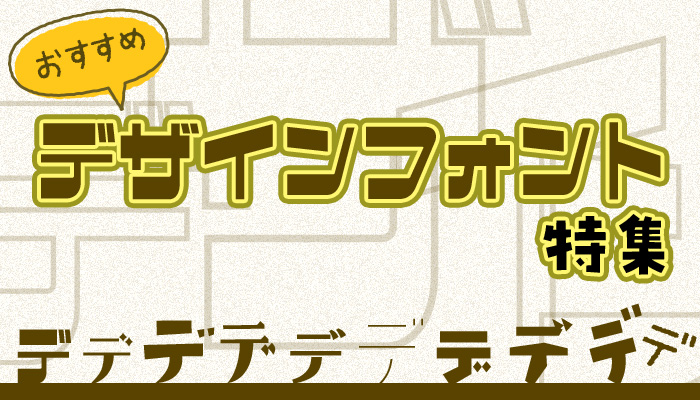
タイトルや見出しに最適! 個性が光るデザインフォントをご紹介
どっしりと太く強いインパクトがあるものから、かたちがユニークなもの、ゆるっとたリラックス感が楽しいフォントまで、色んな表情をもつデザインフォント。各ブランドから様々な雰囲気や特徴のデザインフォントを厳選してご紹介します。
注目を集めたいコピー、タイトル、見出しから、ポスター、チラシ、カタログ、Webサイト、動画、テロップ、アニメーションまで、いろんなシーンで活躍します。
デザインフォントでワンランクアップしたデザインを作りましょう!
鈴木メモ
空とひこうき
万年筆でさらりと書いたようなインクのようなにじみを生かしたはしり書きフォント。
花とちょうちょ
ペンで書いた手書き文字がベースのフォント。右上りの勢いと何より可愛らしいリアル手書き感が特徴。
パンダベーカリー
手描きのような自然なリズム感と見出しやパッケージにも最適なしっかりとした太さがある書体。
デザインシグナル
DSきりぎりす
切り文字のような大胆さを持ったデザインシグナルの一番人気。
DSあかり
角ばった律儀なフォルムと、明るく軽やかな雰囲気を両立する書体。
DSストロング
岩石のような固さ、力強さの中にも優しさを感じる、太く元気な書体。
ダイナフォント
DFロマン雪 A/B/立体
大正末期から昭和初期にかけての古典ロマンの雰囲気を再現した書体。
DF綜藝体 W5/W7/W9
ゴシック体をベースに独特のポップさを生みだしたデザイン書体。
DF金文体 W2/W3/W5
中国戦国時代の金文を元に神秘性や独創性を高め現代的な感覚で仕上げた書体。
楽フォント
遊妖体 (ゆうようたい)
点には抑揚、はらいには独特のカーブとユニークな遊び心に溢れ、どの文字も見ていて飽きないような書体。
凛松体 (りんしょうたい)
書道作品における毛筆の運びと墨によるダイナミックなウエイト表現にモダンなエッジを加えて、端正な面持ちの中にもしっかりとした芯が感じられる書体。
親剛体 (しんごうたい)
縦画と横画の線幅のコントラストによって生み出される圧倒的インパクトと、滑らかでやわらかいカーブの組み合わせが特徴的な書体。
ヤマナカデザインワークス
やわらかドラゴン
強くもあり、どこか柔らかい。そんなイメージの書体。インパクトを持たせたい時、優しい印象を持たせたい時に。
こまどり+
小さくかわいい小鳥のイメージで作成した書体。本文よりも、ちょっとした言葉や見出しに使うと、紙面がカワイイ雰囲気に。
ぱぐのみんちょ
ゆるい感じの書体。全グリフが変則的なサイズをしているので、仮名はプロポーショナル化してベタうちした際になるべく自然に見えるようにしています。
モップスタジオ
ミウラゴチック プロポ R
手書きっぽい柔らかさと暖かさを持ちながら、スタンダードなゴシック体のように使用できる書体。日本語部分にも固有の文字幅が設定された自然な並びを実現します。
ミウラLinerOtf R
ちくちくと繊細な印象の、可愛らしい人気フォントです。手で丁寧に書いたような微妙なゆらぎが特徴。
ミウラ見出しLinerOtf R
滲みのようなチリチリを強調し、ミウラLinerの線を強く太めにした書体。
FONT1000